Những font chữ viết tay đang dần trở nên phổ biến hơn bao giờ hết. Và đây là 47 font chữ viết tay tuyệt vời mà bạn hoàn toàn có thể download miễn phí.
Nếu bạn cần một font chữ viết tay cho dự án của mình, hãy tìm ở ngay bài viết này. Khi chúng ta nói về những font chữ viết tay, chúng ta không chỉ đang đề cập đến một phong cách của typography; mà là một kiểu chữ cần rất nhiều kỹ năng. Nó cũng là một dạng font chữ viết thảo nhưng ít gò bó hơn và dựa vào những đường nét tự do.
Gần đây, phong cách typography này xuất hiện nhiều hơn bao giờ hết, được ưa thích hơn trong in ấn cũng như trong kỹ thuật số so với các font truyền thống. Dưới đây là top font chữ miễn phí mang phong cách viết tay mà bạn có thể sẽ thích và download chúng đấy. Hãy cùng RGB.vn tham khảo nha.
01. Yunus
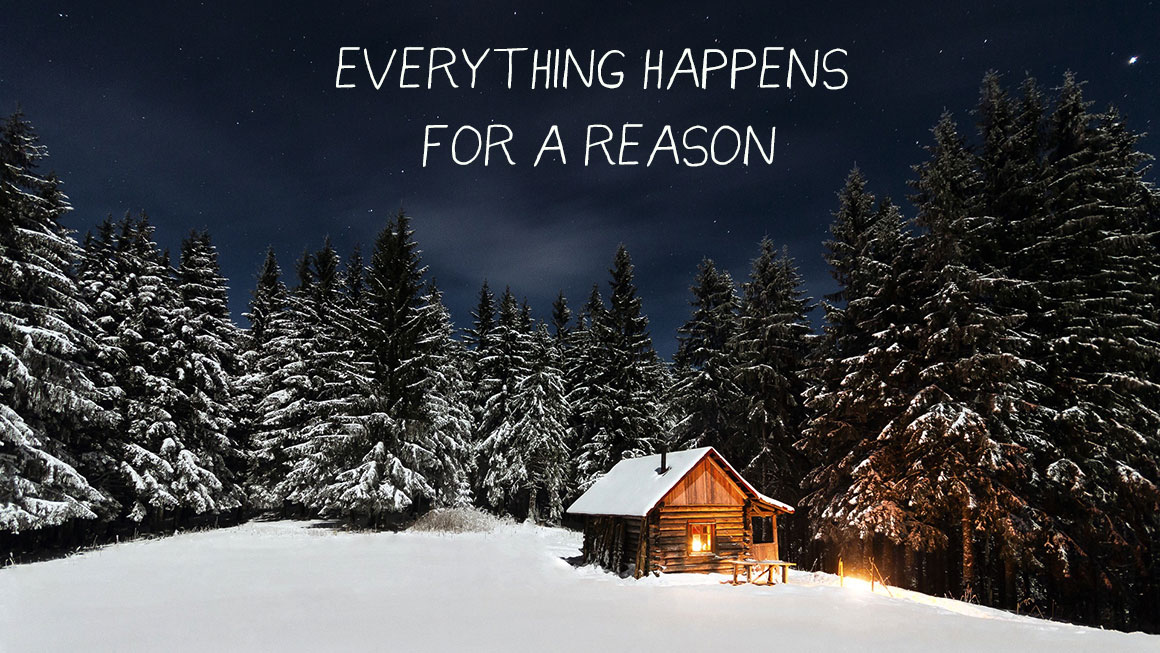
Font Yunus được tạo ra bởi graphic designer Faraz Ahmad. “Mỗi một chữ cái đã được nắn nót rất cẩn thận để làm câu chữ của bạn trông thật đẹp,” tâm sự của tác giả trên Behance. Kiểu chữ này được tạo nên từ rất nhiều yếu tố, khiến nó phù hợp với tất cả các phong cách của những dự án sáng tạo.
02. Cavorting
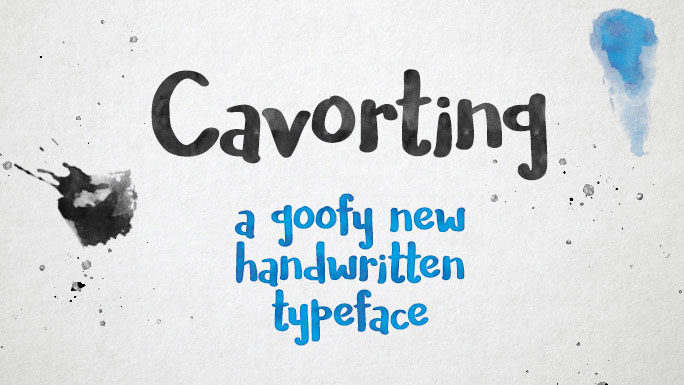
“Đây chính là font chữ một-ngày,” Missy Meyer – người sáng tạo ra kiểu chữ Cavorting này nói. “Tôi đã tạo ra mẫu chữ và thực hiện tất cả những việc như canh khoảng cách giữa các ký tự và các nhóm chữ chỉ trong vòng một ngày.” Và như Meyer nói, kiểu chữ viết tay ‘goofy’ này có thể được sử dụng cho cả mục đích cá nhân và thương mại.
03. Mightype
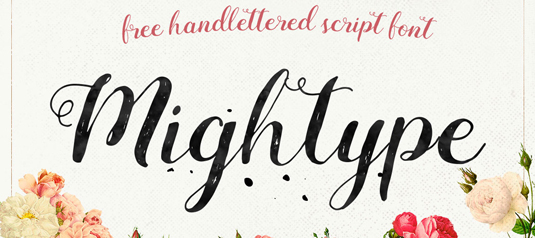
Miễn phí cho mục đích cá nhân và thương mại, Mightype đã được tạo ra bởi một nhóm tại AF Studio. Là một font chữ viết tay, Mightype là lựa chọn tuyệt vời cho việc thiết kế bao bì, xây dựng thương hiệu và hơn thế nữa.
04. Futuracha
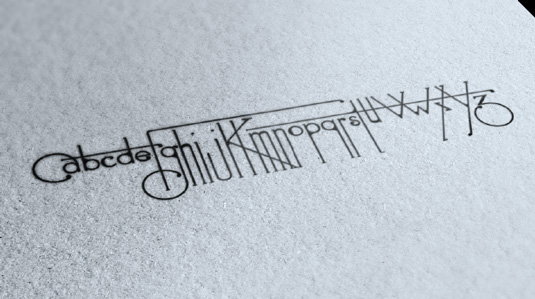
Hãy thêm vào một chút thanh lịch cho thiết kế của bạn với font viết tay Futuracha tuyệt đẹp này.
Một nhóm những designer tò mò chuyên khám phá đã lập nên nhóm holy và đó cũng chính là nhóm thiết kế đứng sau font viết tay Futuracha tuyệt đẹp này. Trang The holy trên Behance nói rằng: “Cái tên là sự kết hợp của từ future (tương lai) và cucaracha (nghĩa là con gián trong tiếng Tây Ban Nha). “Thiết kế này dựa trên font Futura book cơ bản. Cạnh chữ được mở rộng ra một cách hoàn toàn khác biệt để gợi nhắc đến phong cách Art deco.”
05. Reis
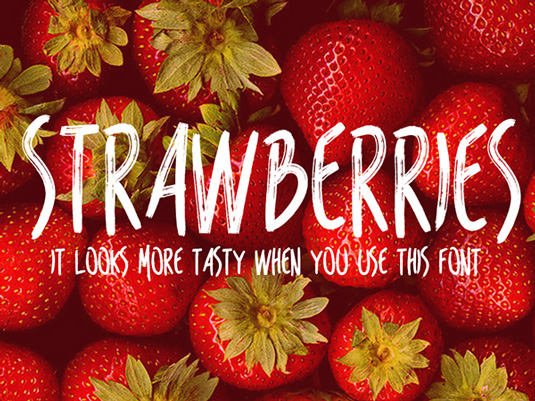
Thiết kế viết tay Reis được tạo ra bởi Marcelo Reis Melo. Là một font tuyệt vời cho poster, logo và hơn thế, Reis miễn phí cho mục đích cá nhân và thương mại, và dĩ nhiên, sự đóng góp này của tác giả, luôn đáng được trân trọng.
06. Bellaboo
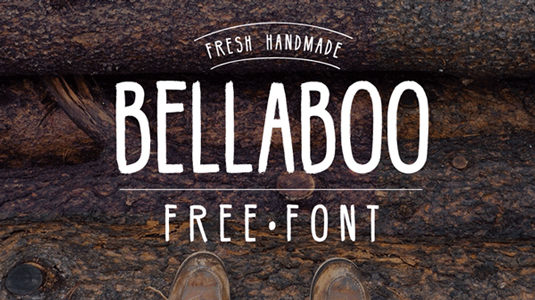
Cần một font viết tay độc quyền cho dự án mới nhất? Bellaboo của Marcelo Reis Melo có thể chính là những gì bạn đang tìm kiếm. Là một thiết kế táo bạo, Bellaboo rất tuyệt cho việc tạo ra các tiêu đề bắt mắt, poster.
07. Ludicrous
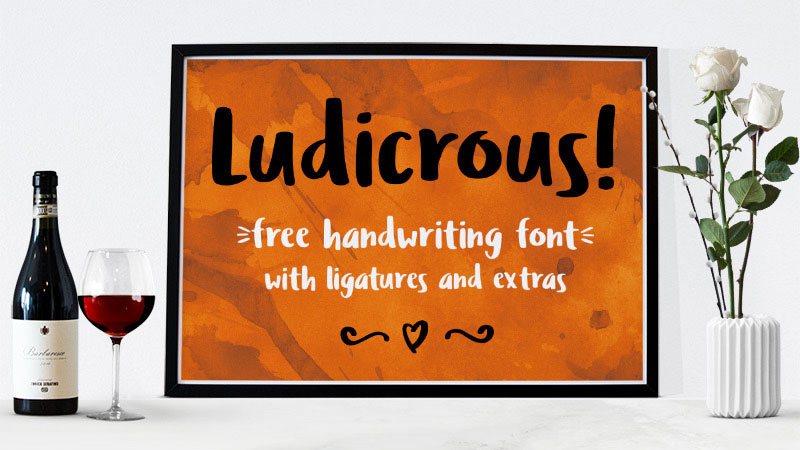
Là một font viết tay miễn phí khác của Missy Meyer, Ludicrous rất tuyệt trong việc gợi ra cảm giác viết tay chân thật. Miễn phí cho cả mục đích cá nhân và thương mại, sự đóng góp của tác giả là rất đáng trân trọng.
08. Fofer
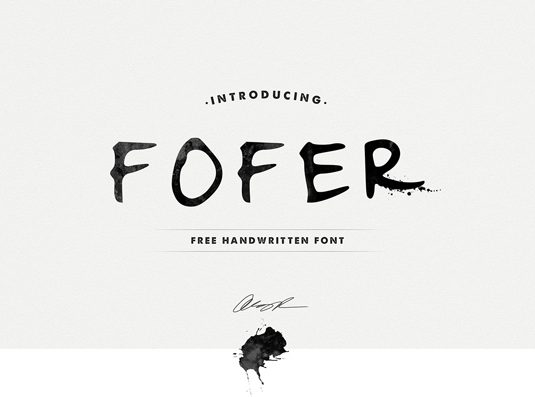
Fofer được tạo ra bởi nhà sáng lập của Mousse Creative và giám đốc sáng tạo Angie Raess. “Đôi khi những dự án tốt nhất lại được tạo ra từ những khó khăn,” Raess viết trên Behance. “Chúng tôi cần một font chữ đặc biệt nhưng không thể tìm thấy. Còn cách nào tốt hơn việc sử dụng chính chữ viết tay của mình?” Fofer có thể được download trên Behance, tất cả những gì Raess cần trả lại chỉ là một cái tweet đơn giản mà thôi.
09. California Sans
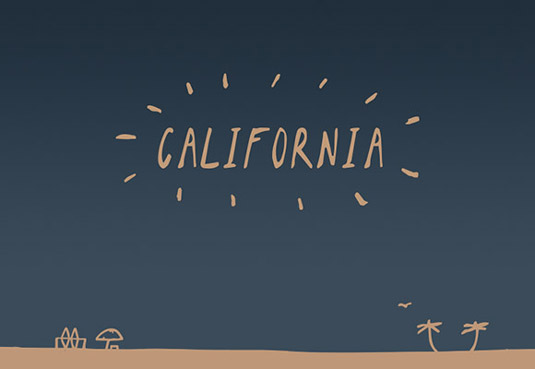
California Sans là một font viết tay, được tạo ra bởi designer gốc Mexico Noe Araujo. Được miễn phí download, thiết kế này bao gồm bộ đầy đủ các chữ cái viết hoa và thường, chữ số và vô số ký tự đặc biệt.
10. Ruffle Beauty
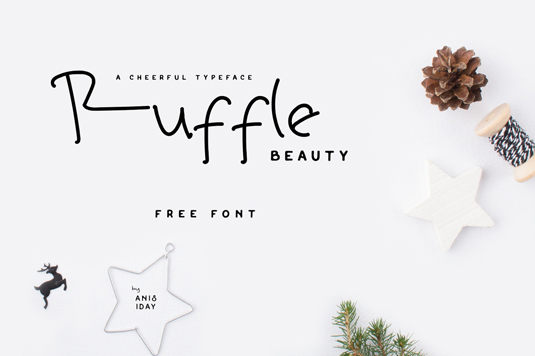
Nếu bạn đang tìm một font viết tay tinh nghịch, giải pháp lần này chính là Ruffle Beauty của Anis Iday. Rất lý tưởng cho các thiết kế poster, Ruffle Beauty miễn phí cho cả mục đích cá nhân và thương mại.
11. Skinny
Đến nay, font viết tay này là thiết kế phổ biến nhất trên mạng của artist được biết đến với tên notfon1234. Bản update cuối cùng của thiết kế đã được gọt giũa lại khoảng cách và nét chữ, và hiện tại font chữ này hoàn toàn miễn phí cho mục đích thương mại.
12. Gunny Rewritten
Dựa trên font Gunny Handwriting cũ, type designer Vit Condak cho ra một font viết tay miễn phí mới, đó là Gunny Rewritten. Không hài lòng với phiên bản gốc, Condak đã hoàn toàn tạo dựng lại thiết kế này và giờ đây nó được download miễn phí cho tất cả những ai cảm thấy thích thú.
13. Halo Handletter
Font viết tay thanh nhã này được phát triển bởi graphic designer Mario Arturo. Là một trong hơn 20 font chữ được thiết kế bởi Arturo, người chuyên về các font chữ viết tay bay bướm, Halo Handletter chính là một ví dụ hoàn hảo sau cùng. Font chỉ được sử dụng miễn phí cho mục đích phi thương mại.
14. LeHand
LeHand là font chữ đầu tiên được tạo ra bởi indieferdie. Font LeHand phản ánh phong cách viết tay tinh nghịch, điều sẽ khiến các dự án thiết kế mới của bạn trở nên tuyệt vời hơn. Là một web designer và branding designer, chúng tôi nghĩ rằng indieferdie sẽ còn có nhiều những công việc truyền cảm hứng phía trước hơn nữa.
46. Dickie
Freelance designer David Ellis đã tạo ra font viết tay Dickie bằng cách sử dụng MyscriptFont, một công cụ online cho phép bạn tạo ra font chữ vector từ chính chữ viết tay của bạn. “Đó là một điểm bắt đầu tuyệt vời khi bạn không có nhiều font viết tay để sử dụng, và quy trình khá nhanh,” Ellis nói.
47. Soulmarker
Font chữ viết tay SoulMarker đã được tạo ra bởi nhà thiết kế đồ họa và vẽ tranh minh họa Faraz Ahmad. Font có 2 định dạng: mỏng và đậm, SoulMarker rất thích hợp cho các dự án kỹ thuật số và in ấn.